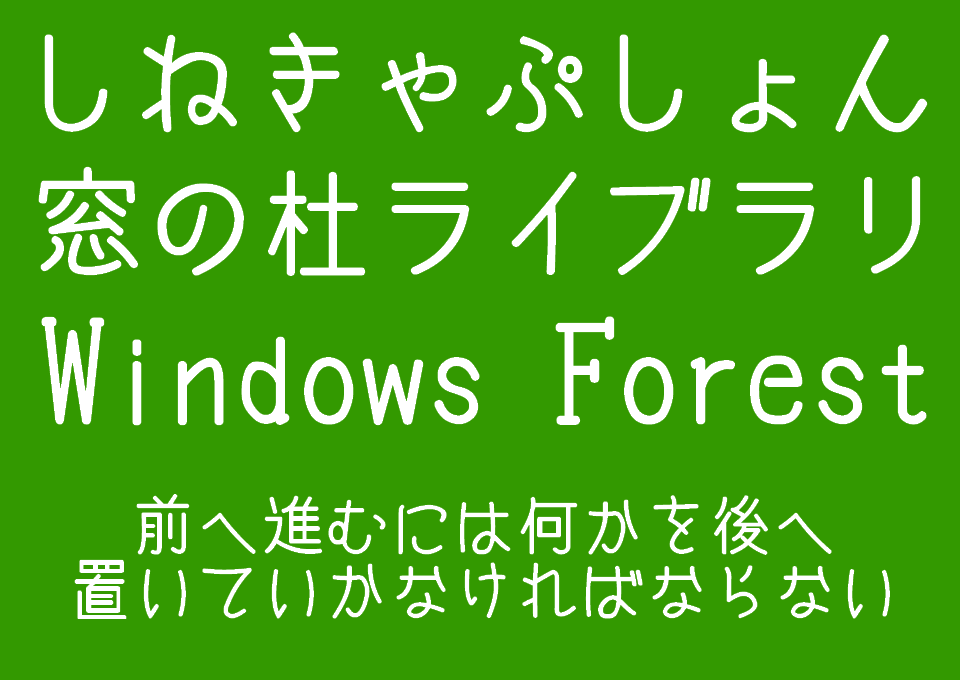
商用時も無料な定番フォント! 洋画の手書き字幕を模した「しねきゃぷしょん」
10年以上も愛され続ける傑作、カフェのメニューなどにも最適
映画館で上映される洋画の字幕には通常、ゴシック体などの機械的なフォントではなく、手書き風のフォントが採用されている。フォントワークス社が掲載しているインタビュー記事によれば、スティーヴン・スピルバーグが監督した2001年公開のSF映画『A.I.』で初めて字幕用のフォントを使用するまで、現ワーナー・ブラザース社の映画では書体デザイナーが実際に手書きしていたという。
「しねきゃぷしょん」は、そんな洋画字幕特有の手書き文字を再現した日本語フォント。筆者が試し打ちしたところ、ひらがな、カタカナ、英数字、記号のほか、JIS第一水準漢字のすべてと同第二水準以降の一部を収録しているようだ。
ひらがなのアンバランスな骨格や反った画線、大きい濁点・半濁点が特徴であり、全体的に文字の造りを強調するデザインとなっている。これは、無声チャンバラ映画の手書き字幕を復刻したフォント「うずまさ本丸ゴシックmini」にも通じる演出であり、その時代から続く伝統なのかもしれない。